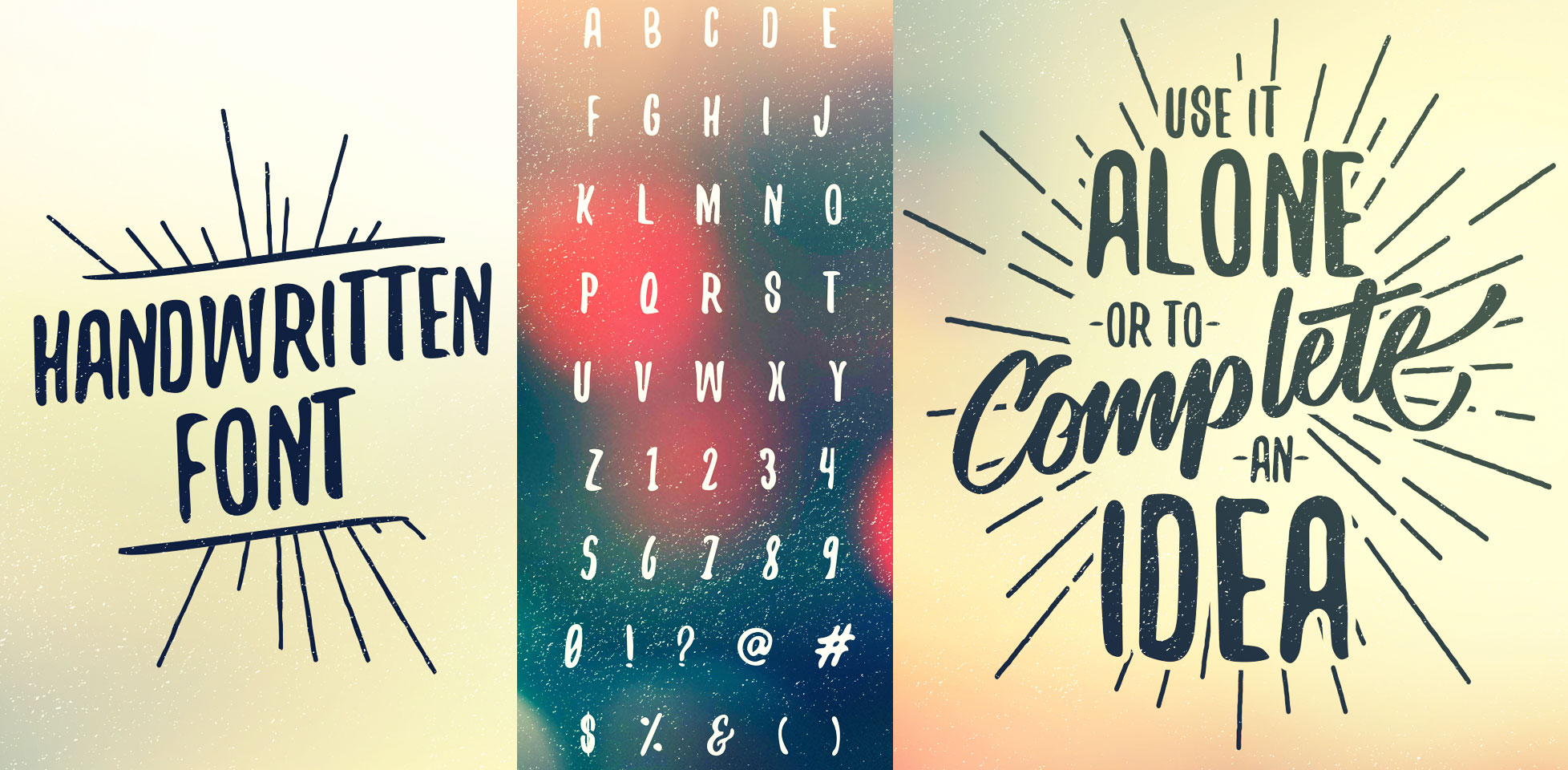
El 2015 ha resultado ser un gran año para las fuentes. Los diseñadores de tipografías se mostraron muy prolíficos, y existen nuevos diseños para cada proyecto, a menudo gratuitos, o al menos con alguna opción libre para descarga.
Hay un par de tendencias dominantes esta temporada: por un lado la vuelta a los estilos étnicos y folclóricos (como la colorida Tripel Six, o la encantadora Quirko); y por el otro, una visión más humanista de las sans-serifs (como Qontra).
A continuación, una muestra de las mejores fuentes de lo que va del año, con su respectivo link de descarga: